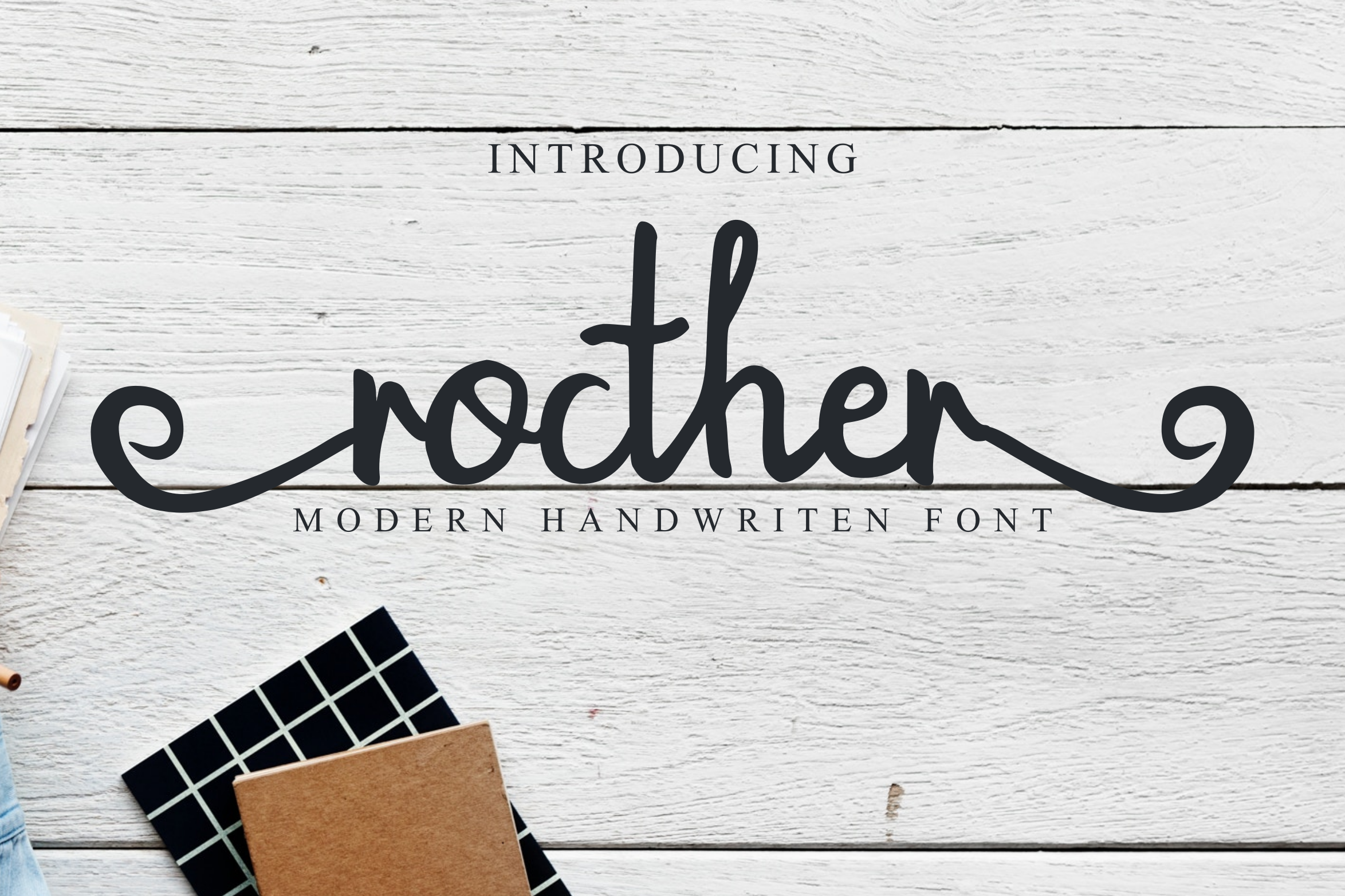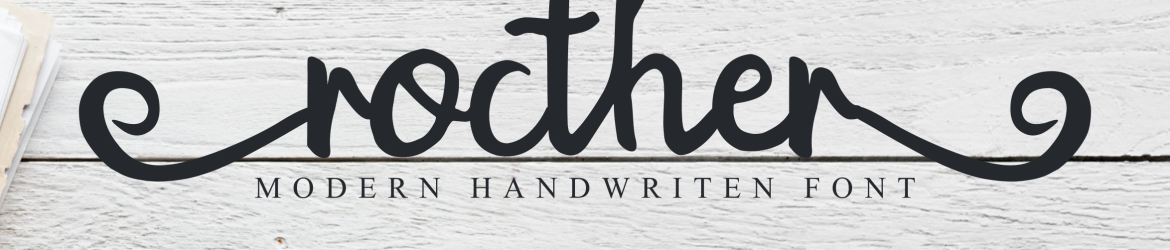
Rocther Script Font – Download Grátis
A Rocther é uma elegante fonte de escrever cursiva criada com uma caneta-pen de espessura média que vai tornar seu design mais belo e suave. A sua caligrafia fluida e suavizada pode ser usada em qualquer projeto gráfico, seja em um logotipo sofisticado ou em um texto editorial envolvente. Seja para uma apresentação elegante de negócios ou para personalizar cartões de aniversário com um toque romântico, a Rocther oferece o charme dos desenhos artesanais e do trabalho manual. Esta fonte é ideal para quem procura algo único que combine perfeitamente tanto em projetos digitais quanto em impressos, destacando seu design gráfico na hora de transmitir mensagens e experiências ao público.